/RETRO FONTS/
* Những font này phù hợp với edit vintage, retro style . Nếu có thể áp dụng vào horror style và graphic thì càng tốt.
I,American Captain
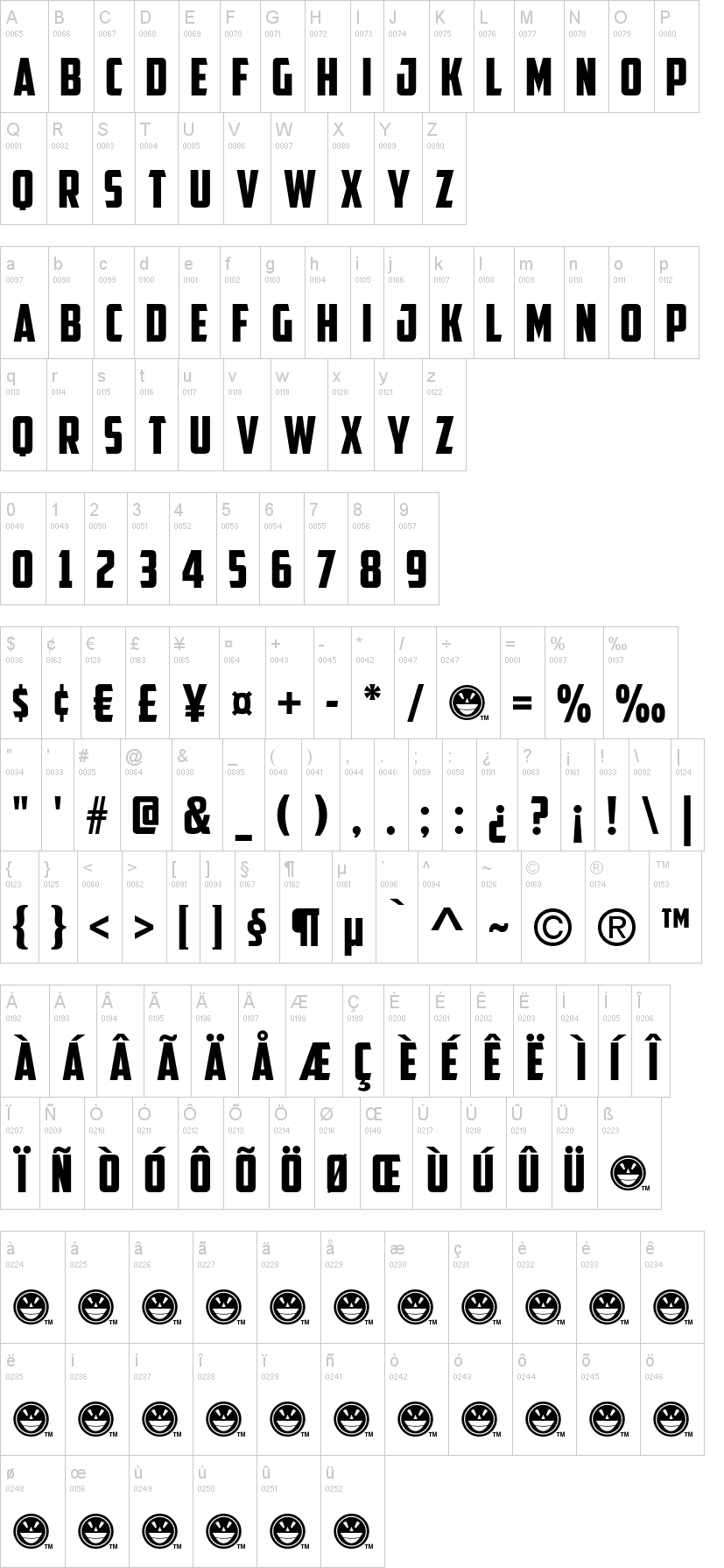
II, RiesLing
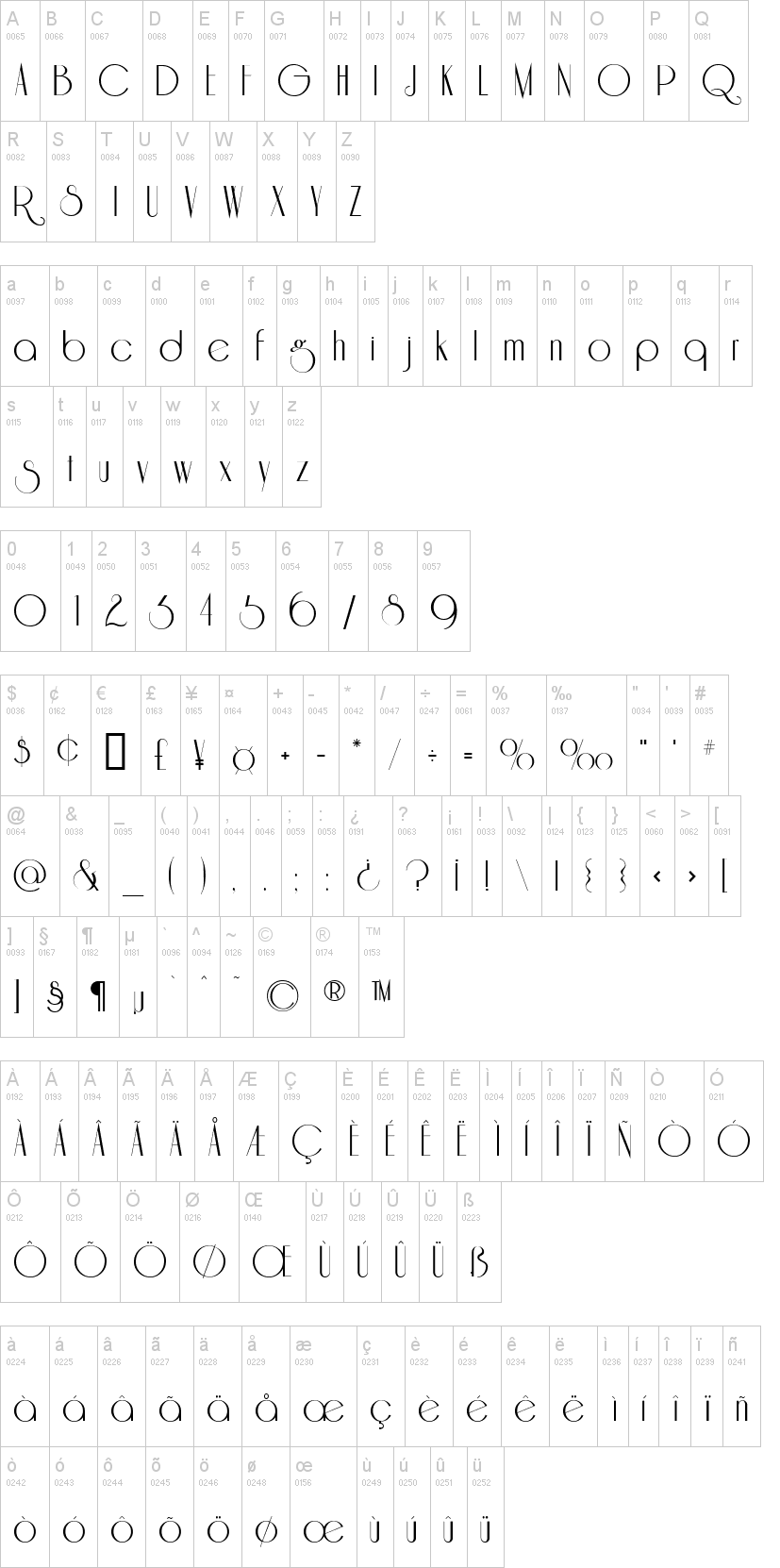
III,Annabel
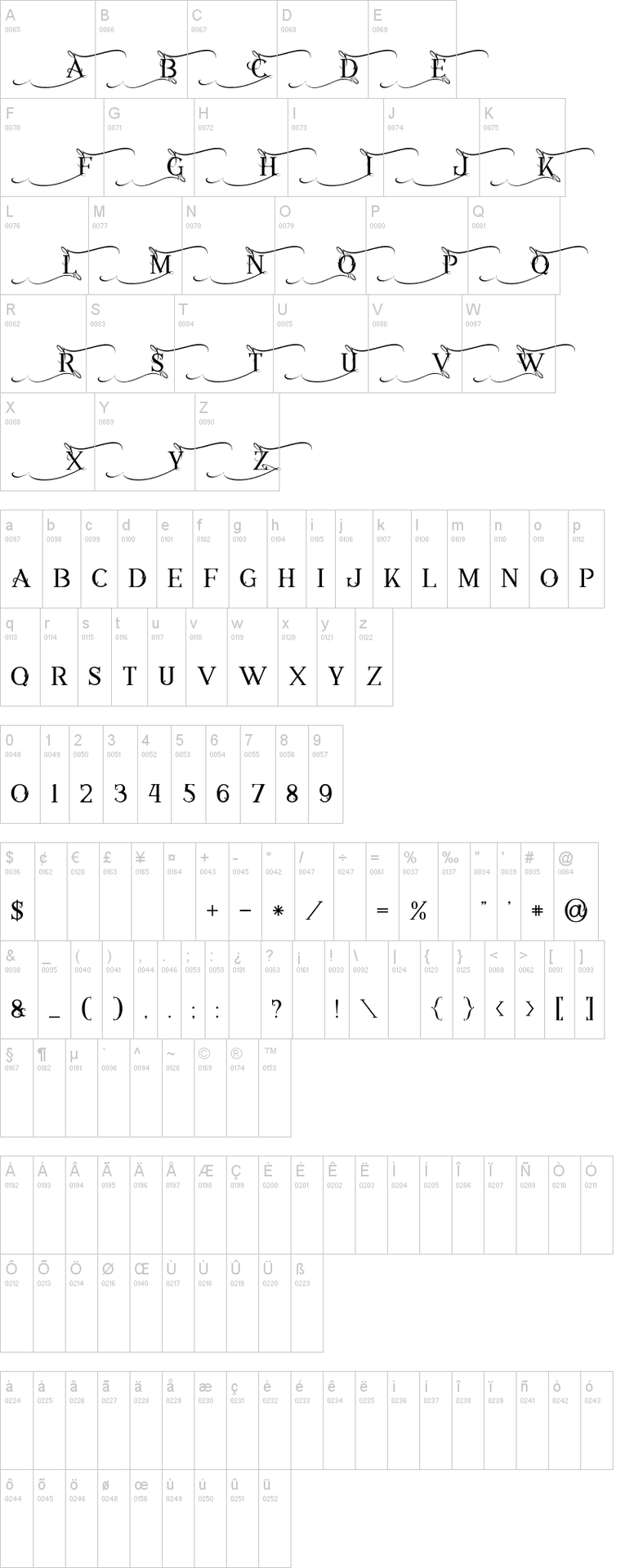
IV, Steelworks
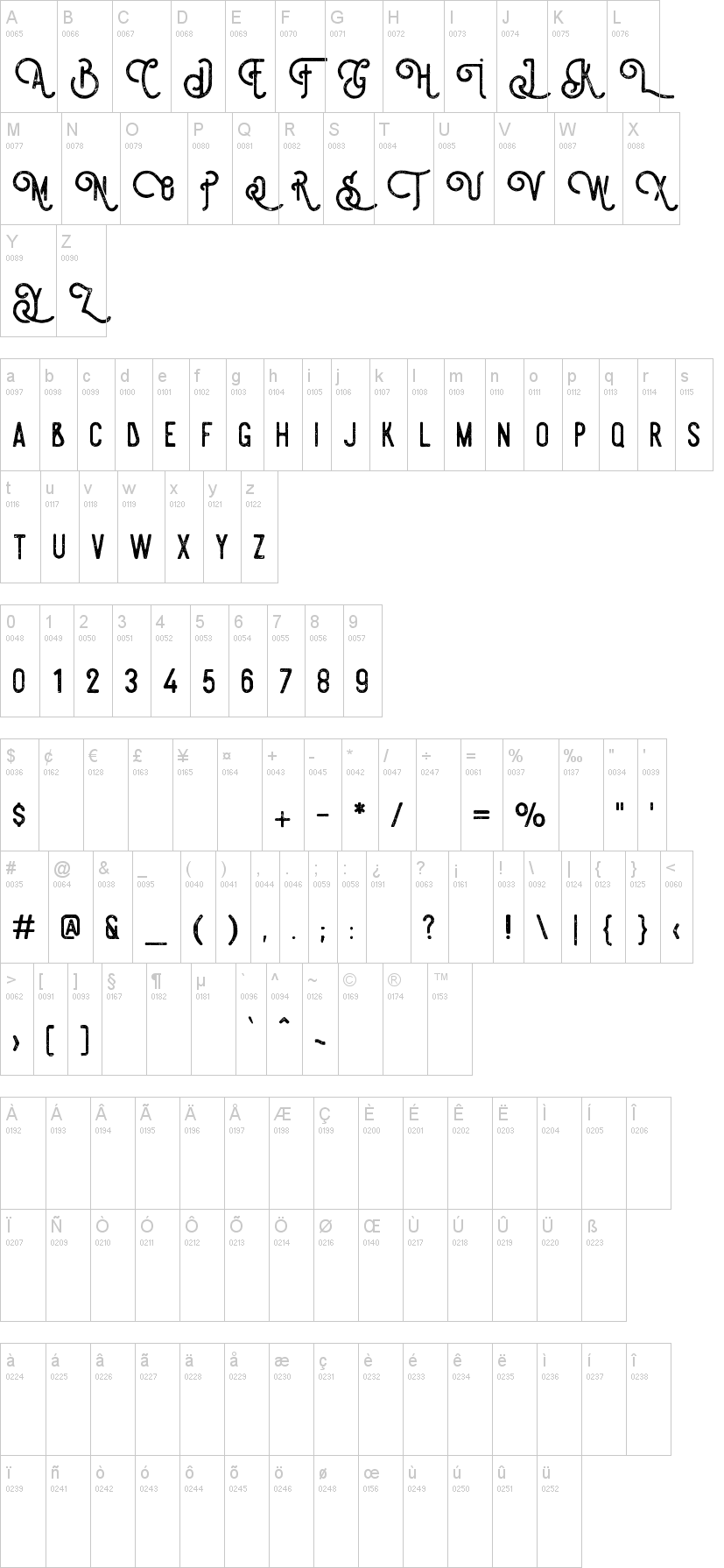
V, Festival Budaya XXXI
VI,Antique Book Cover
VII,Celestinal
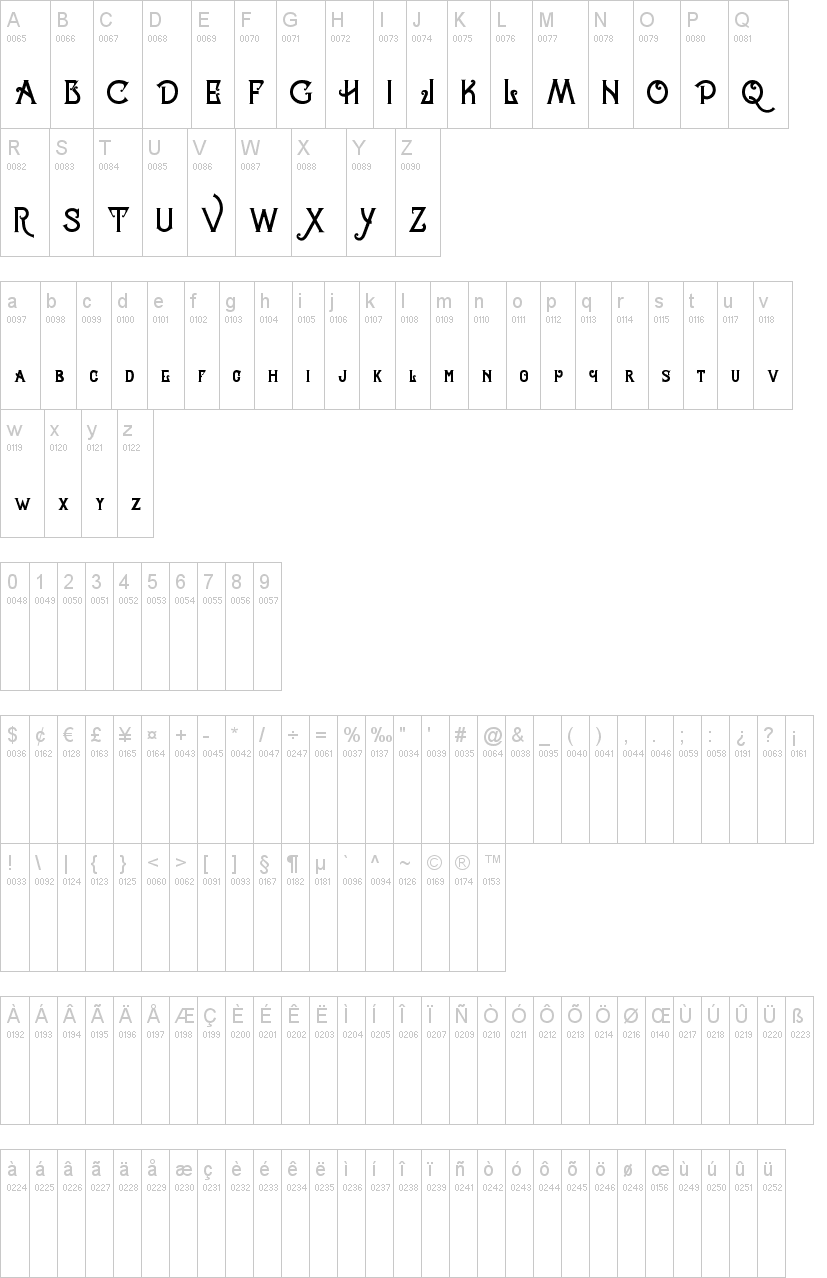
VIII, Star Black Inline
IX,Metropos
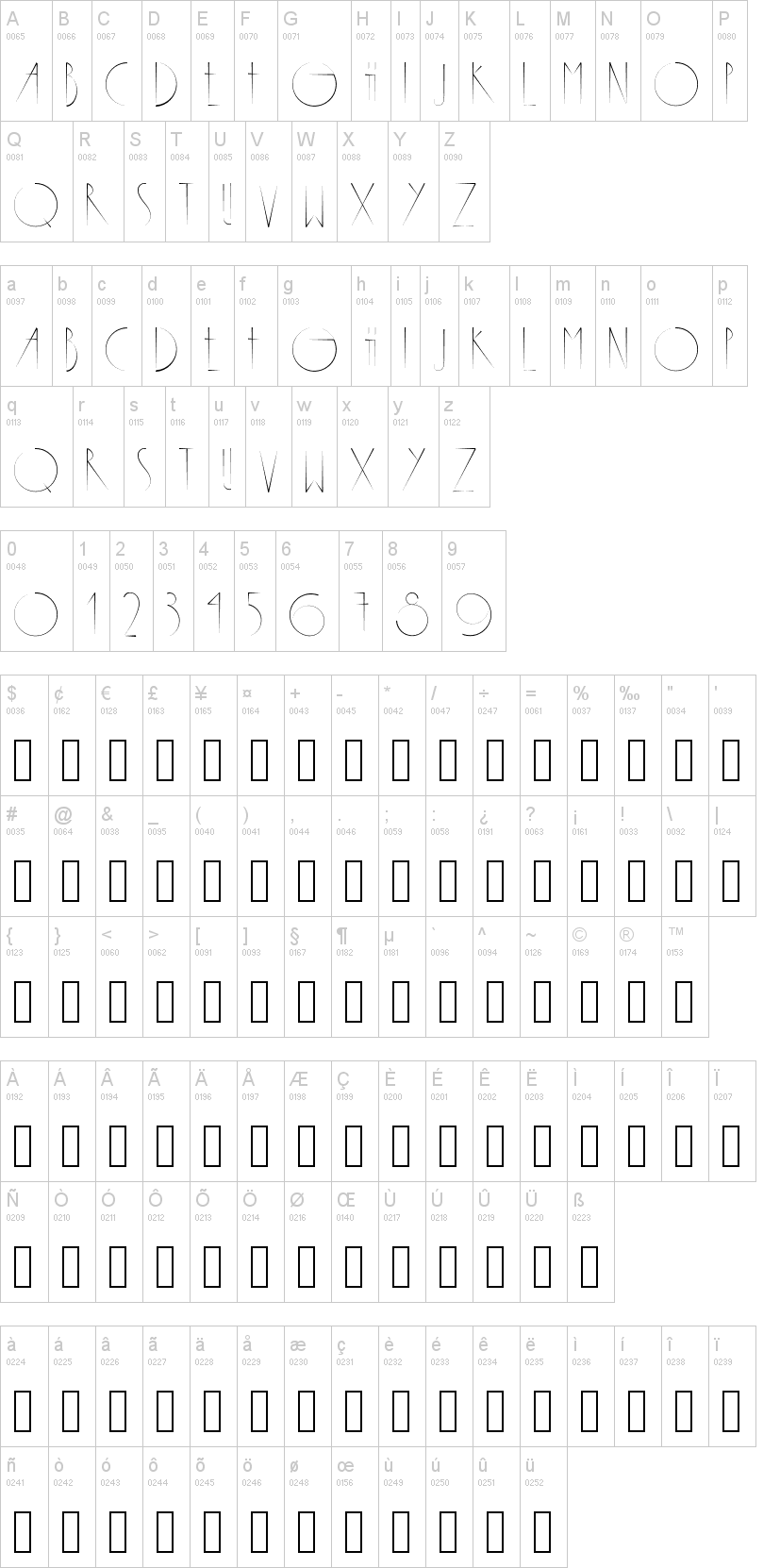
X, A pompadour
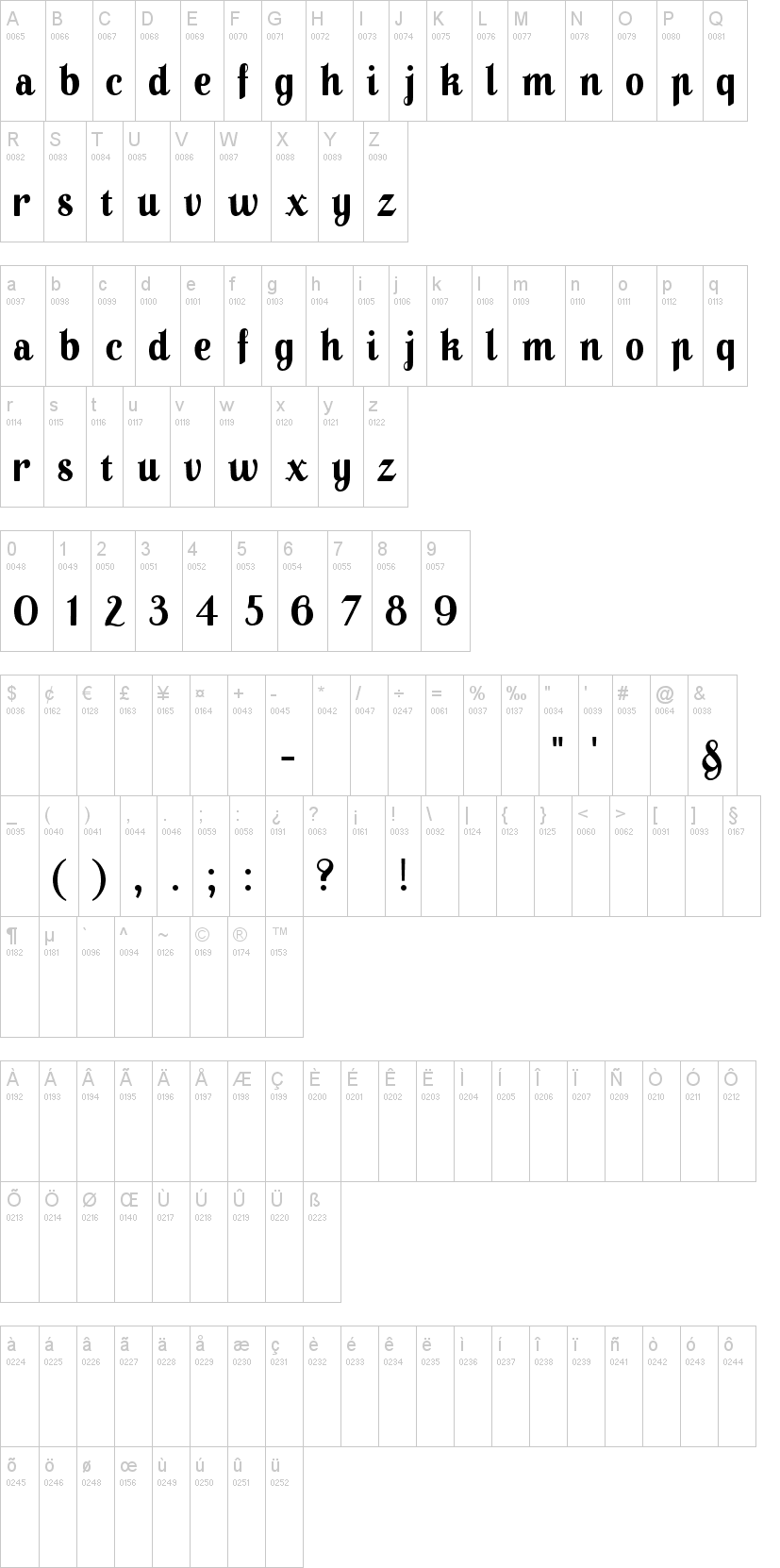
XI, Victorian Palor
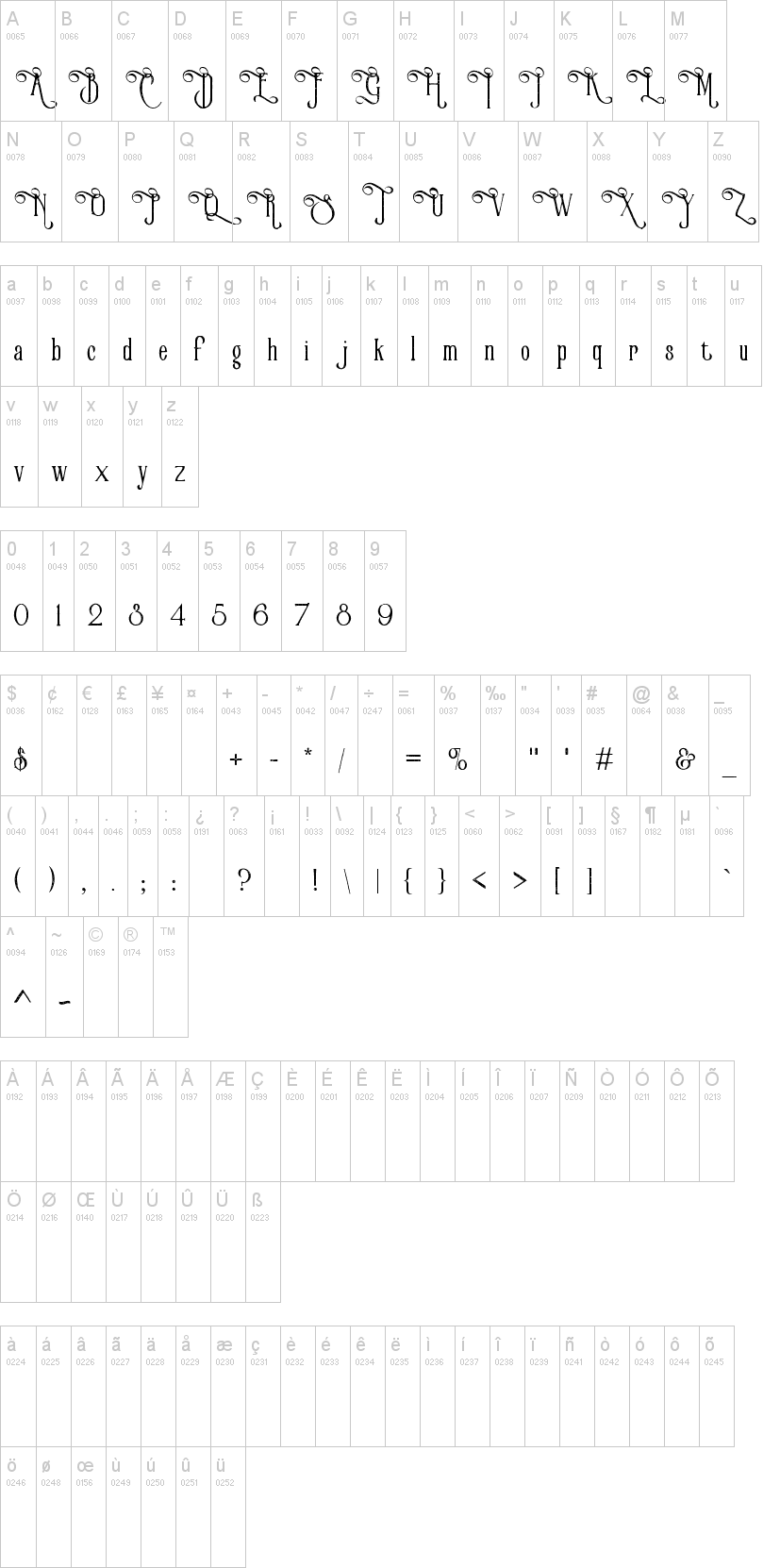
XII, Breamcatcher
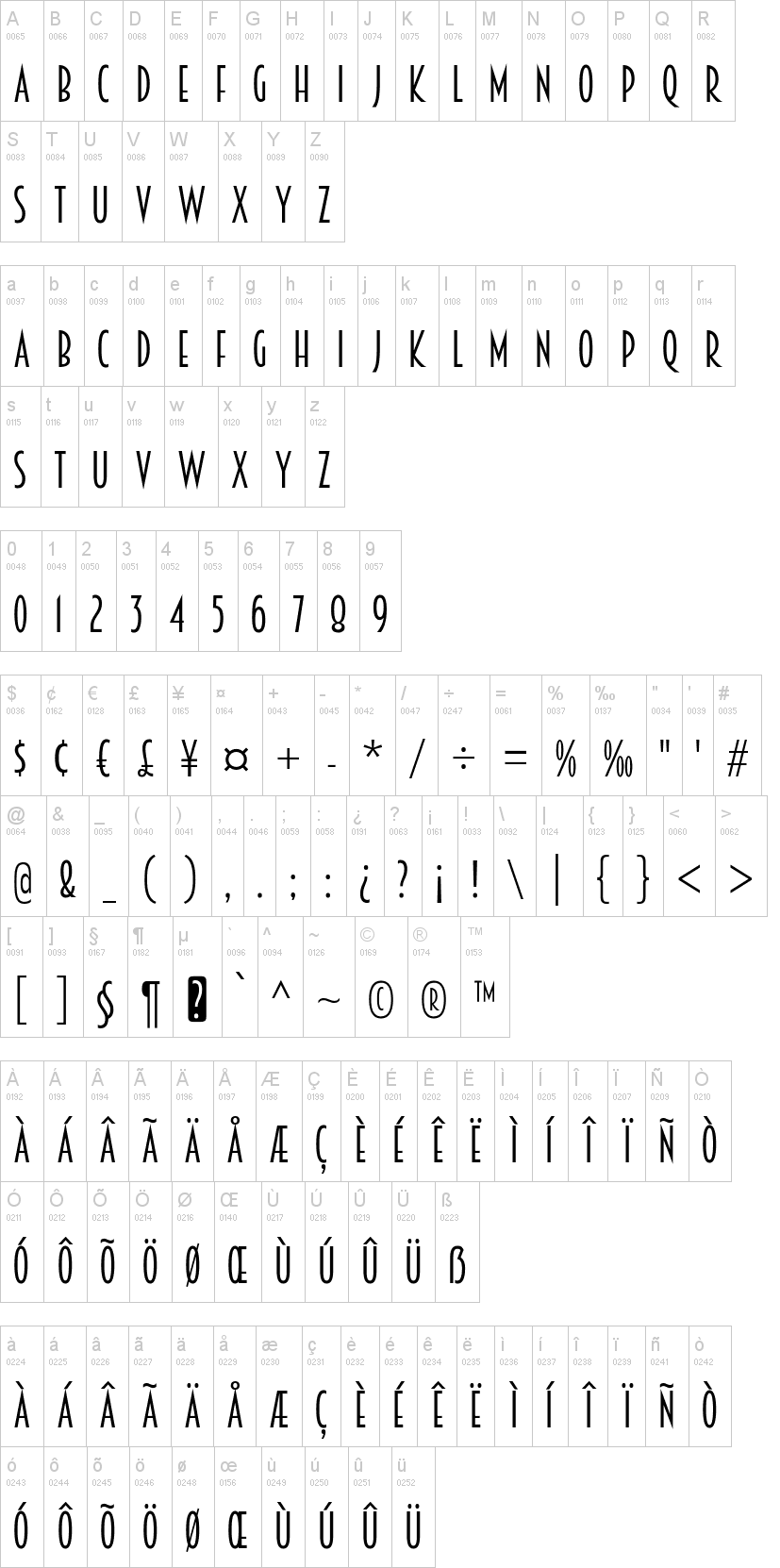
XIII,RiotSquad
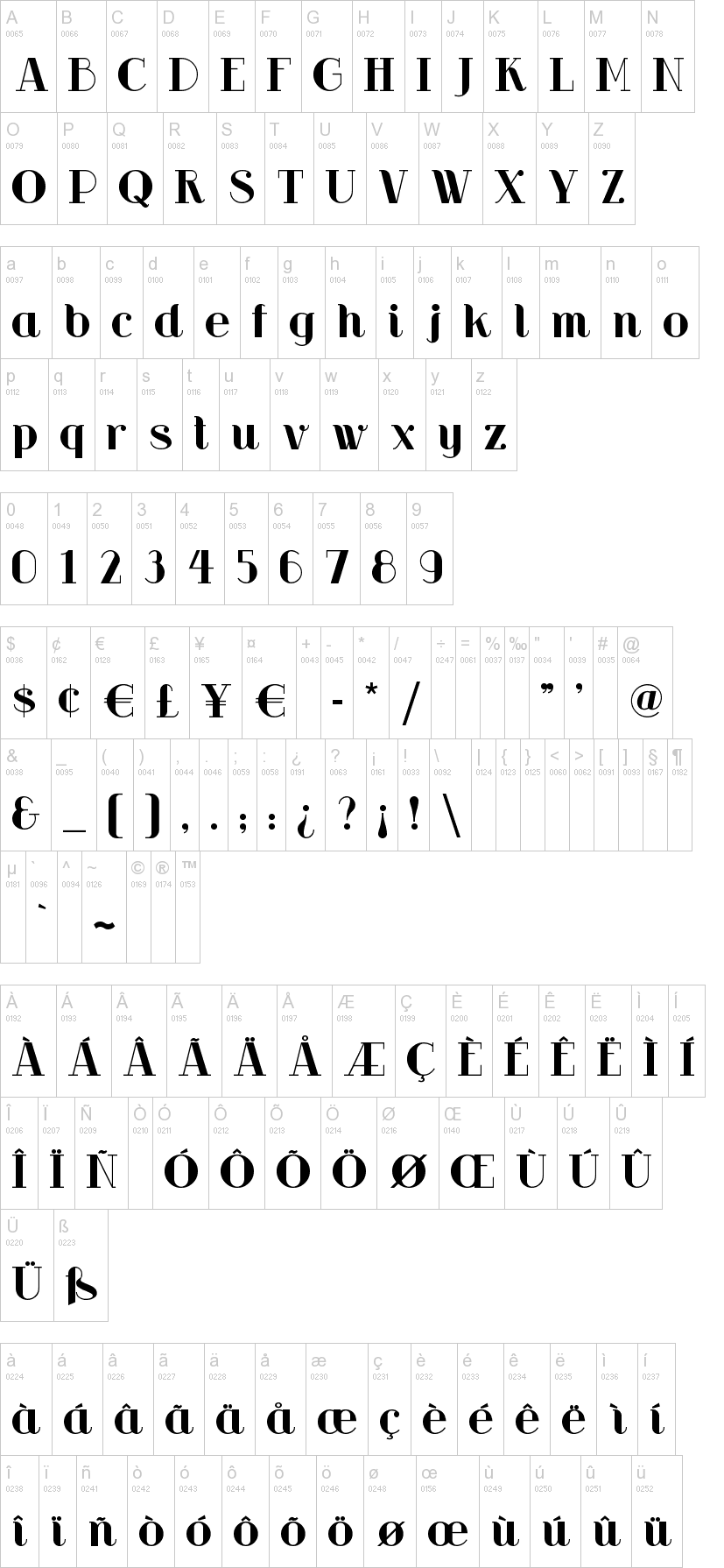
XIV, Schluber
XV, Bardo
XVI, Avanti